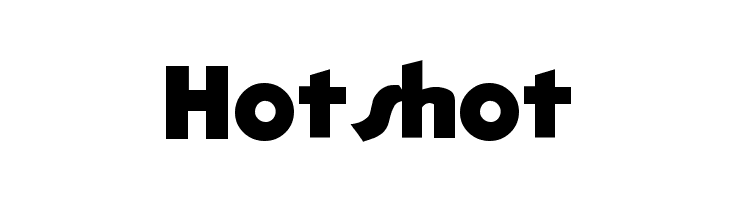
A bold, metallic block serif font with a three-dimensional, industrial look.
A playful, cartoon-like font with characters featuring eyes and ears, perfect for children's designs.
A whimsical font with characters designed as abstract faces.
A lively and dynamic script font with fluid strokes and a playful character.
A bold, playful font with thick, rounded strokes and a lively appearance.
A pixelated, retro-style font with a blocky, geometric design.
A dotted, textured font with a playful and abstract style.
A bold, blackletter-style font with sharp, angular lines and a dramatic presence.
An elegant and ornate decorative font with intricate swirls and flourishes.
A scratchy, hand-drawn font with a textured, artistic style.
A decorative bone-themed font with a shadow effect, perfect for spooky designs.
A bold, geometric font with sharp angles and a futuristic style.
A festive collection of Christmas-themed icons in a playful, decorative style.
A decorative symbol font blending Celtic, astrological, and mythological imagery.
A bold, dynamic handwritten font with brush-like strokes.
A modern, rounded sans-serif font with clean lines and balanced spacing.
A playful, handwritten font with a whimsical and informal style.
A playful, whimsical script font with fluid, dynamic letterforms.
A bold, jagged font with a horror-themed, dripping effect.
A playful, hand-drawn font with tall, narrow letters and a whimsical style.
A camera symbol icon font for digital photography interfaces.
A modern, monospaced font with an extra light weight and geometric design.
A lively, dynamic handwritten font with fluid, interconnected strokes.
A bold, expanded, and italicized font with a rugged, textured appearance.